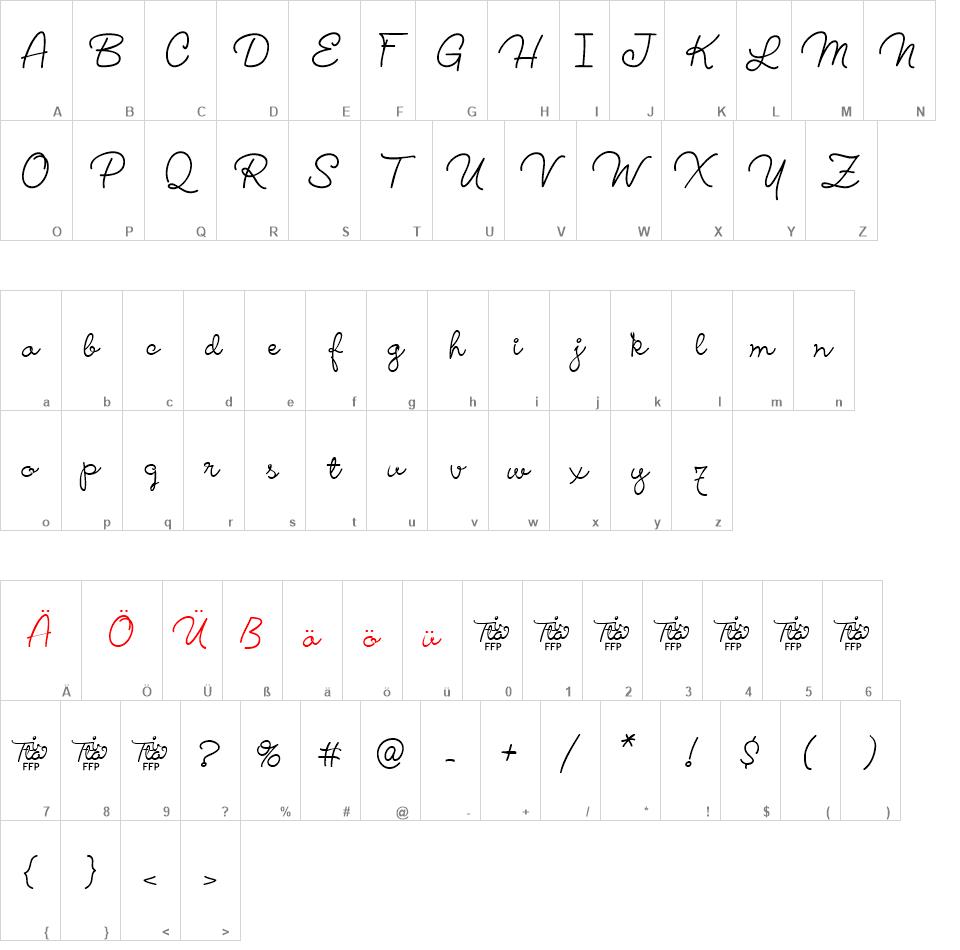
Lucemita
Lucemita font
Lucemita
Handgeschriebene Schrift, die meiner Tante Lucemita gewidmet ist.
• Die kommerzielle Version enthält 2 vollständige Sätze von Großbuchstaben für alternative Titel und einen Kleinbuchstaben für das Ende von Wörtern (Swashes), um benutzerdefinierte Schreibstile zu erstellen.